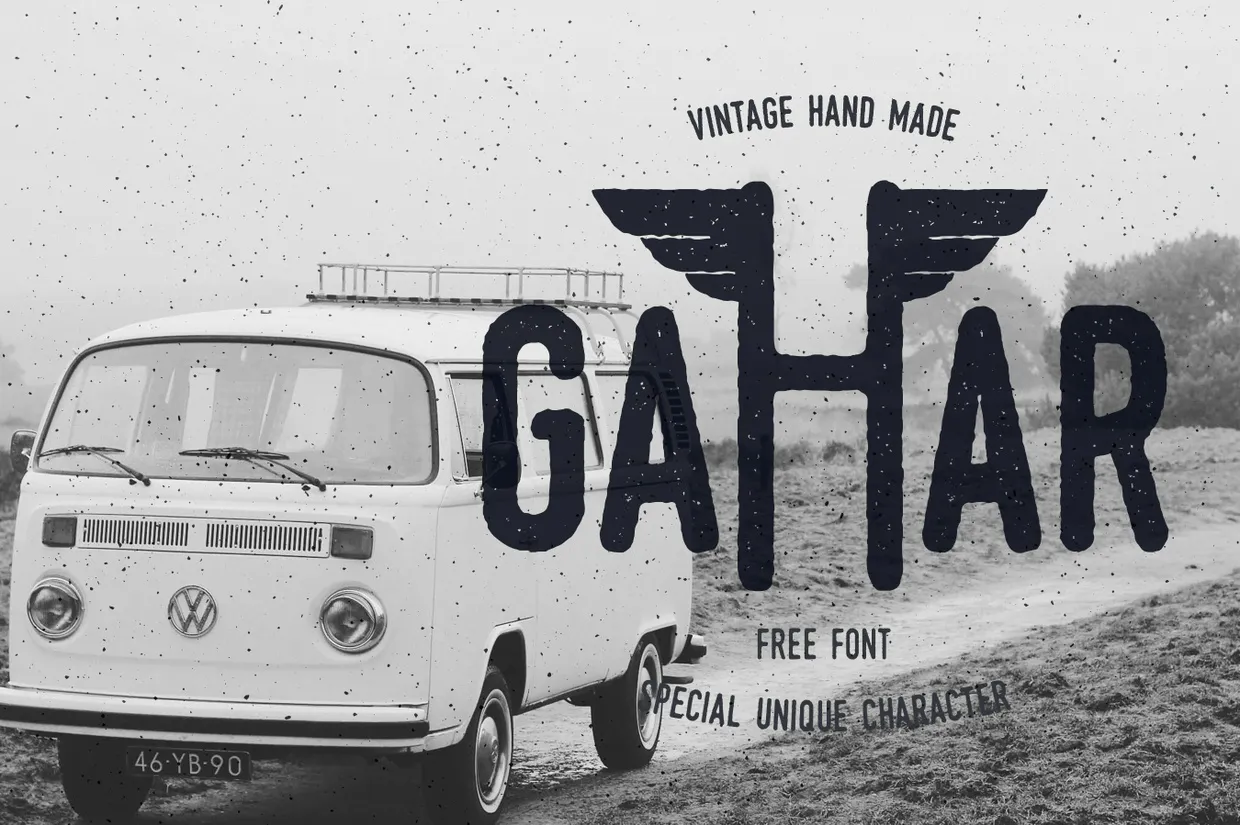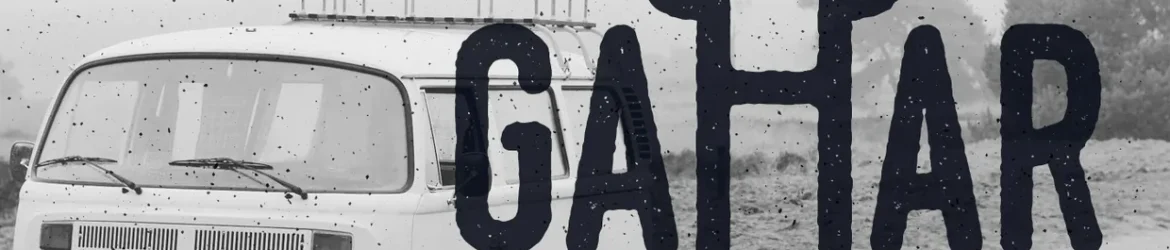
Introduzimos a você uma linda fonte vintage feita à mão, o Gahar Font, projetada e compartilhada por Agga Swistblnk, designer famoso de fontes. Com um aspecto único e sofisticado, esta fonte é perfeita para adicionar um toque autêntico ao seu projeto. Seja para gráficos digitais ou impressos, a Gahar Font oferece linhas elegantes que se destacam em qualquer layout, tornando-a uma escolha ótima tanto para o design de web quanto para aplicativos móveis. Suas formas redondas e detalhes delicados criam um ar vintage único, enquanto sua estética moderna mantém seu charme inovador. Com certeza, a Gahar Font é uma excelente adição à sua coleção de fontes.